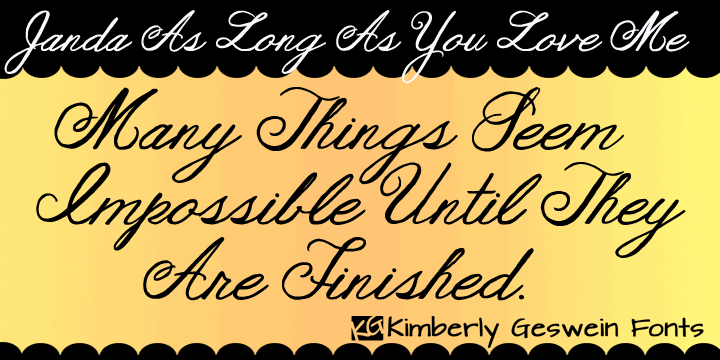
A Janda As Long As You Love Me é uma fonte script que traz nuances e charme para qualquer projeto pessoal ou comercial. Desenvolvida pelo designer Hamilton, esta fonte oferece uma experiência de escrita única e fluida, tornando-a perfeita tanto para gravações exclusivas quanto para criação de designs digitais. Ideal para quem busca um toque especial em seus projetos, a Janda As Long As You Love Me é uma escolha agradável para criar mensagens que chamem atenção. Seja para cartões personalizados, letras do seu blog ou capas de livros inovadoras, esta fonte vai deixar sua obra mais única e memorável. Acreditamos na importância da colaboração, por isso solicitamos um mínimo de contribuição a partir do uso comercial. Essa pequena dádiva fará um grande bem para o designer que criou essa linda fonte, permitindo-lhe dedicar tempo e energia a criar novas criações incríveis. Seja você um estudante ou uma empresa experiente, a Janda As Long As You Love Me é uma fonte perfeita para quem busca expressar seus sentimentos de maneira única. Se tiver interesse em usar esta fonte, sinta-se à vontade para experimentá-la e contribuir quando estiver pronto.